「菜」の見本
「菜」の書き順
11画です。
「菜」のポイント
横幅について
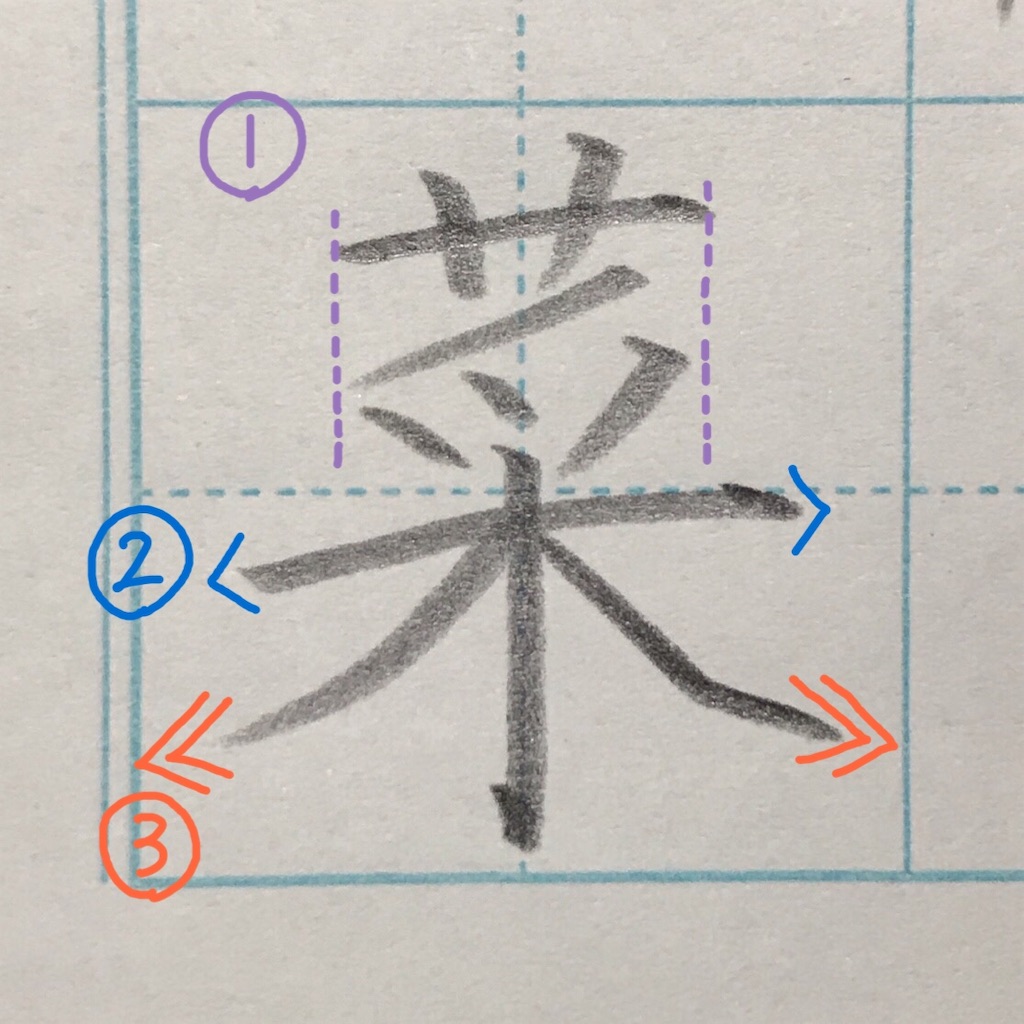
①上半分は幅をそろえる。
(横幅全体の2分の1を目安に)
②長く強調。右上がりに。
③②と同じくらいの幅で払う。
細かいポイント
「くさかかんむり」
④右上がりに。
⑤幅が均等になると◎。
⑥少し高く。
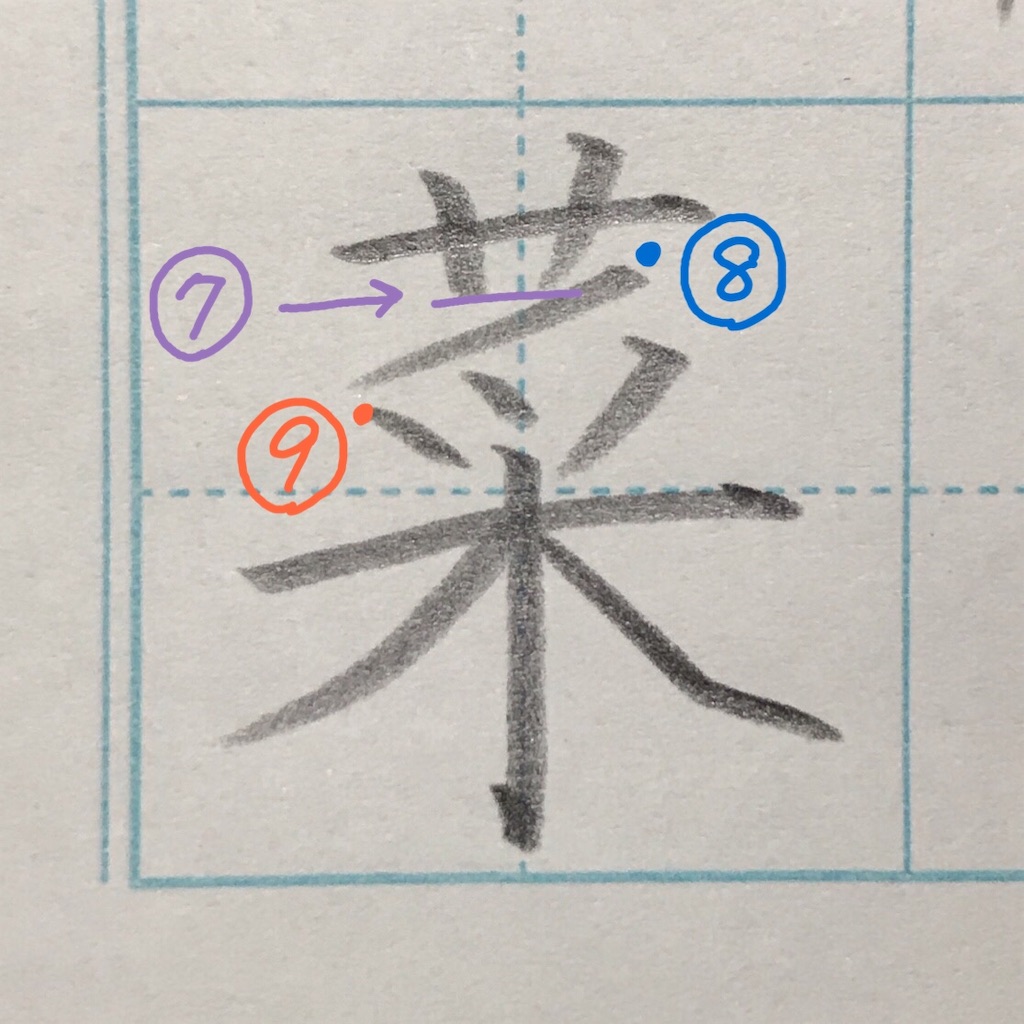
⑦下は揃える。
⑧4画目はくさかかんむりの右の隙間から。
出来るだけ寝かせて、下に響かないように。
⑨1画目の始まり、4画目の終わりと左端を揃えて。
⑩6画目の終わりがほぼ中心に。
「木」の縦画と組み合うように控えめに。
⑪くさかんむりの右端と揃える。
「ツ」部分は上部が3画目に沿って右上がりになると◎。
⑫ここまでが上半分に収まると、「木」が余裕を持って書けます(^-^)
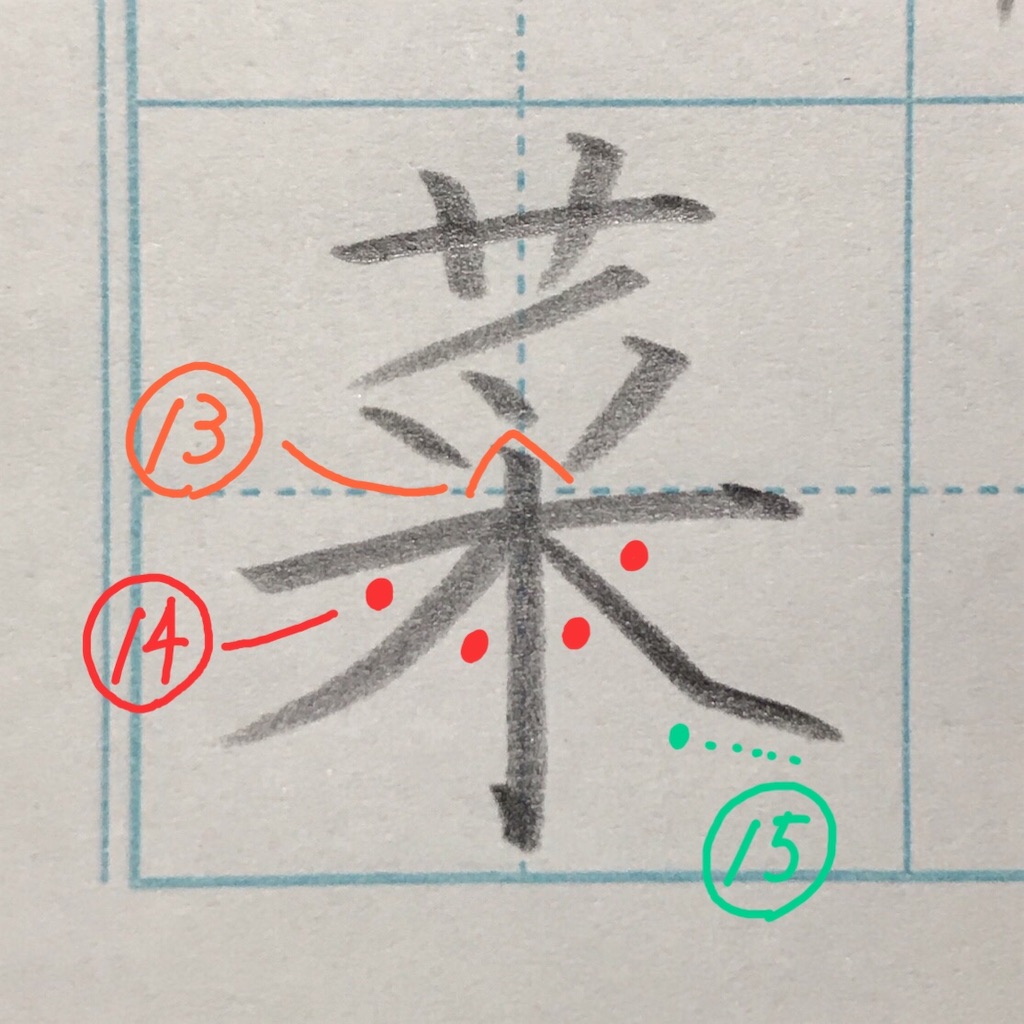
⑬中心に。「ツ」としっかり組み合わせて。
⑭全て同じ広さに。
⑮止めて、払う。
完成!